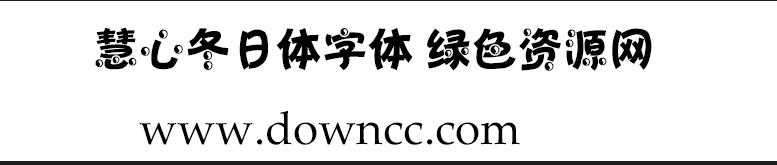
慧心冬日體能夠在手機(jī)上顯示出來,為你帶來最佳的視覺效果,這款字體擁有蘋果與安卓以及電腦英文版字體,讓你能夠快速的在不同平臺(tái)上盡情的使用這款字體,快來綠色資源網(wǎng)下載吧!
我在使用這款字體的時(shí)候覺得十分不錯(cuò)的,能夠讓你手機(jī)系統(tǒng)中的文字變得十分具有立體感,讓你在聊天的時(shí)候感受到最佳的暢快享受!